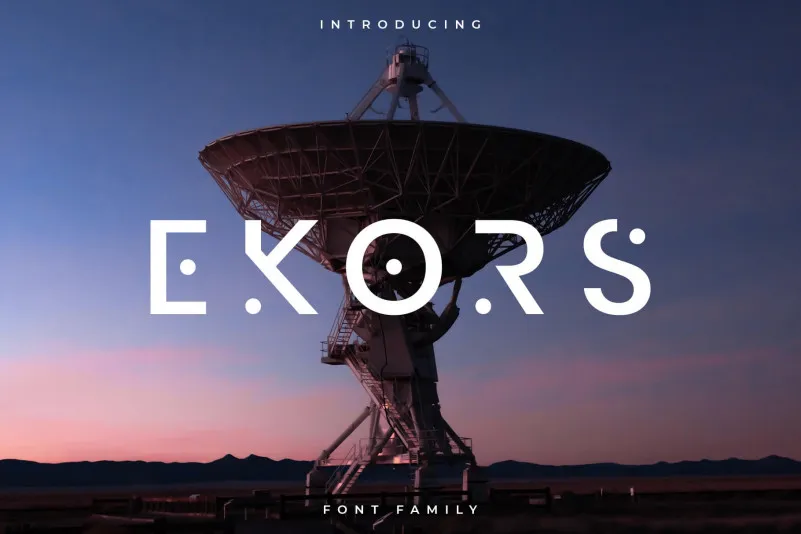
A Ekors Font é uma elegante e moderna tipografia criada por Robin Campistron para quem procura algo mais que a superficialidade dos lances populares. Com seu formato futurista, ângulos geométricos perfeitos e linhas modernas, essa fonte idealmente se alinha com temas tecnológicos, digitais e futuristas. Seu design único e sofisticado deixa qualquer projeto em que seja aplicada brilhar ainda mais. Perfeito para logotipos, cartazes, headlines e tudo o mais que possa precisar de um toque moderno e criativo. Ideal tanto para designers digitais quanto para aqueles com um gosto arquitetônico, essa fonte traz uma nova dimensão a qualquer projeto visual.